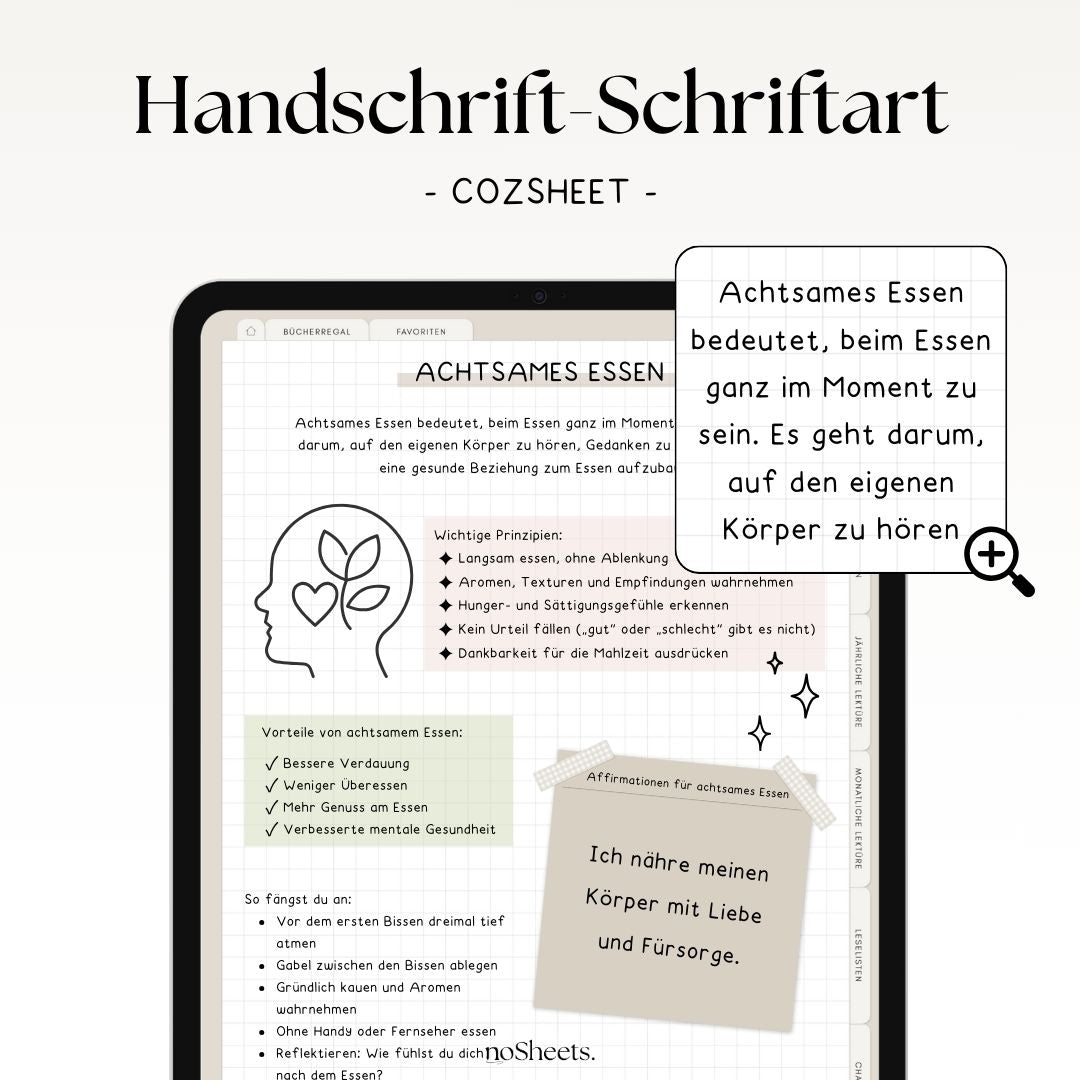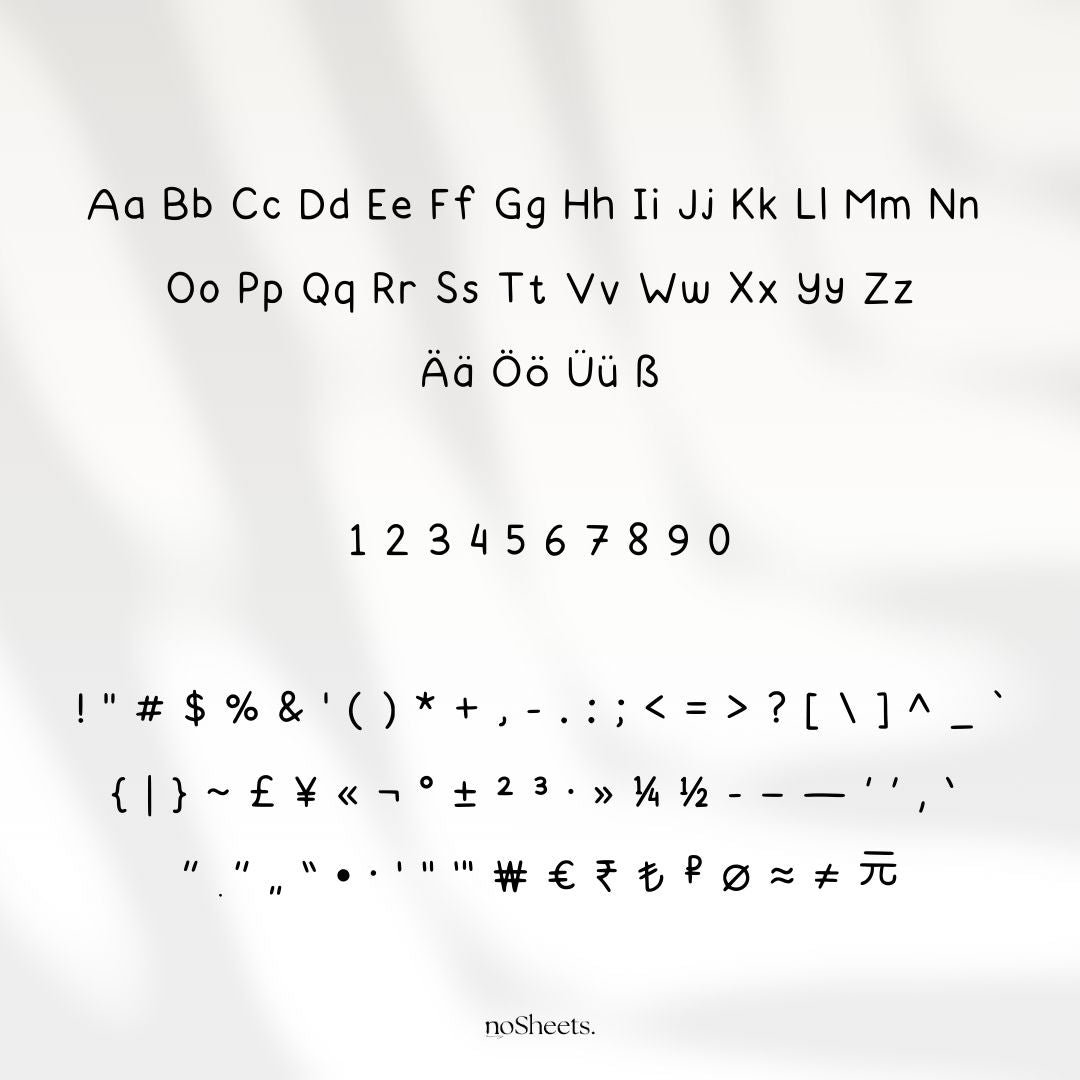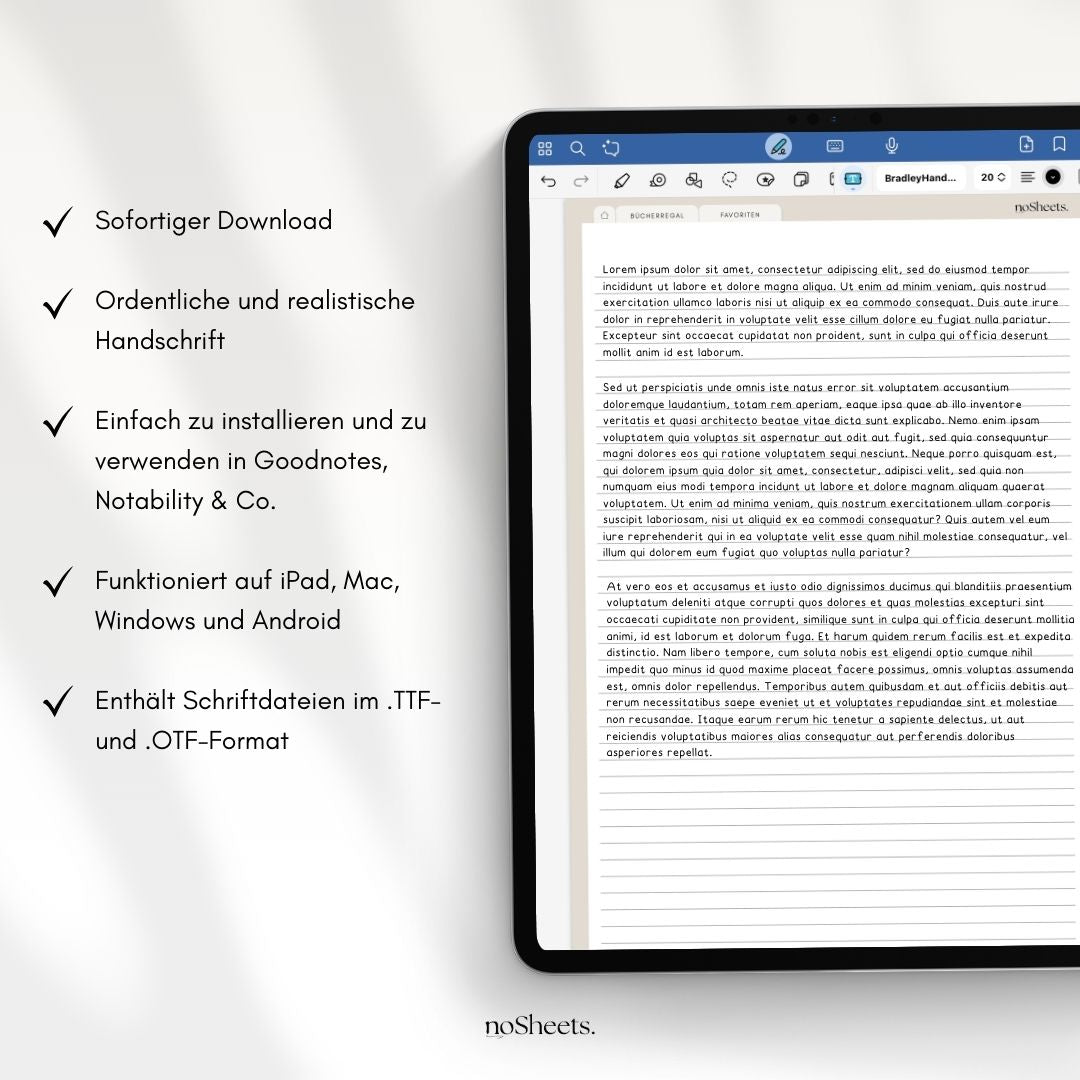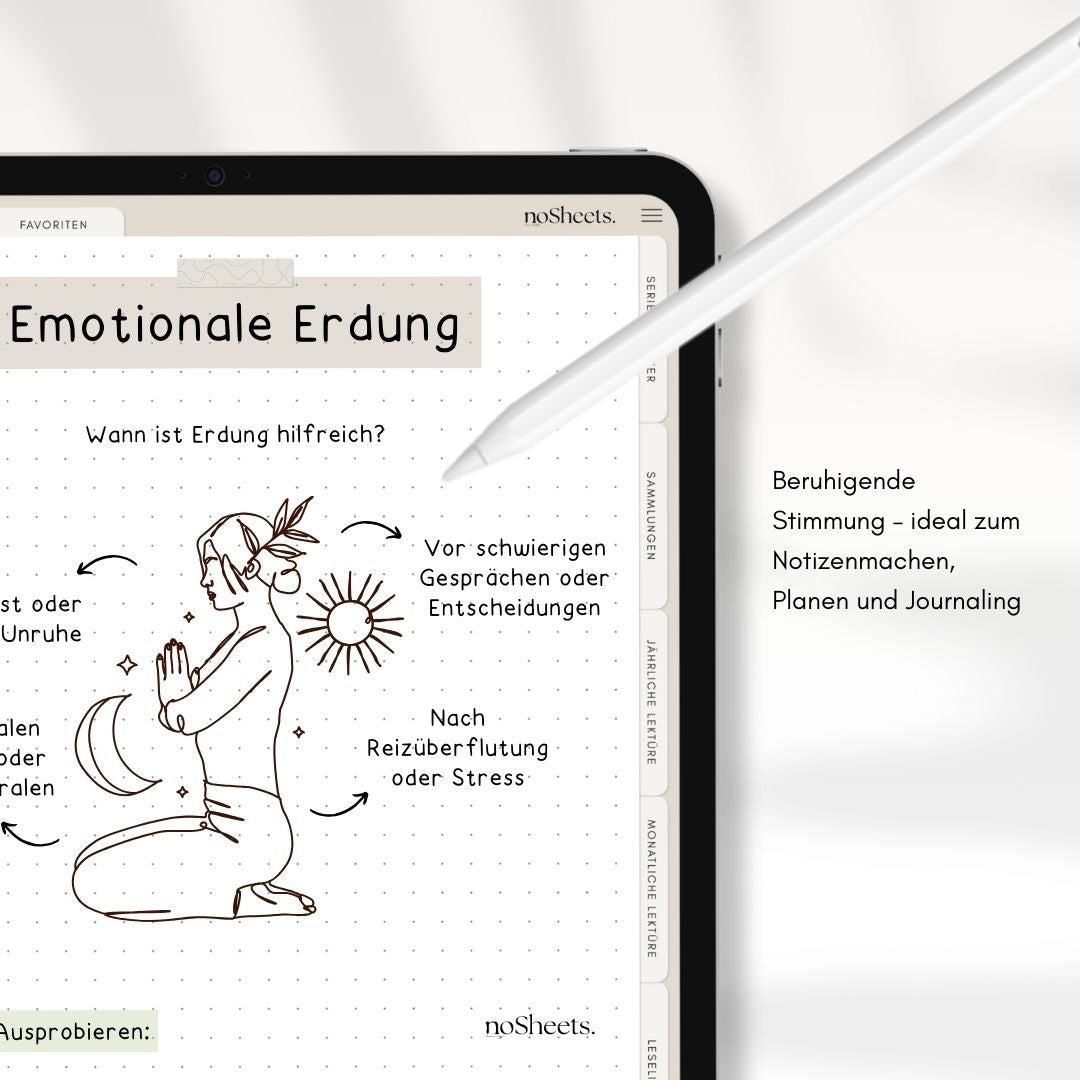
Cozsheet – Komfort trifft Kreativität
Gemütlich. Persönlich. Modern.
Mit Cozsheet schreibst du nicht nur Texte – du inspirierst deine Leser. Runde Formen und eine freundliche Anmutung verleihen jedem digitalen Projekt eine beruhigende, einladende Atmosphäre.
✓ Rund & charmant
Die glyphischen Konturen sind weich gestaltet, wirken angenehm luftig und erinnern an handgeschriebenes Wohlgefühl – ideal für liebevolle digitale Notizen, Planer oder sanfte Titel.
✓ Zeitlos lesbar
Trotz seines verspielten Charakters bleibt Cozsheet klar strukturiert und elegant – perfekt für Projekte, die Gemütlichkeit mit professioneller Lesbarkeit vereinen.
✓ Perfekt für deinen digitalen Alltag
Perfekt für…
✓ Digitale Planer und Scrapbooks
✓ Handgeschriebene Titel & Anmerkungen
✓ Persönliche Designs: Einladungen, Grüße, Social Media